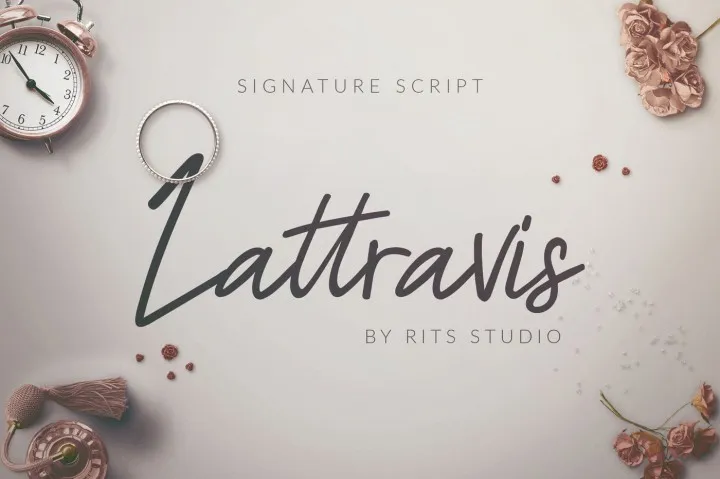
Lattravis Script Font
A Lattravis é uma fonte de script que traz uma experiência única de design. Ela surge do trabalho meticuloso de escrita a mão, usando canetas com tinta líquida. Seu charme reside no seu naturalismo e na sua característica única de flutuar. Esta fonte é perfeita para expressar citações, criar logomarcas ou assinaturas distintivas, estilizar rótulos e embalagens, destacar headlines em blogs ou adicionar um toque personalizado a qualquer projeto design. Com uma fluidez natural e estilo de assinatura simples, a Lattravis oferece uma solução versátil para aqueles que buscam personalidade e sofisticação em seus trabalhos gráficos. Experimente ela agora e revolucionar seu próximo projeto!